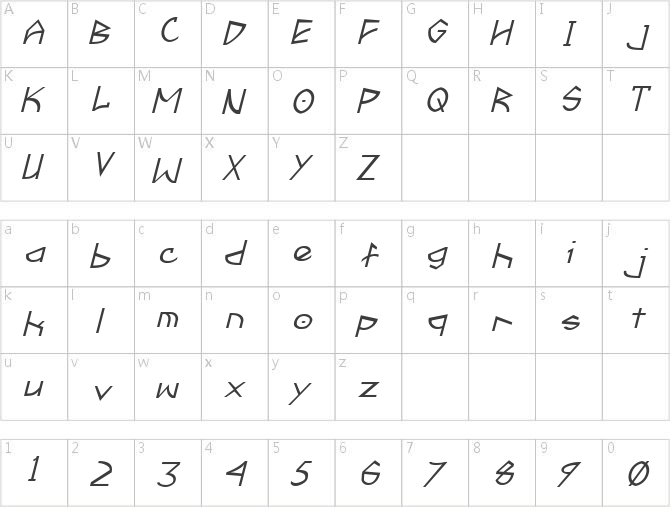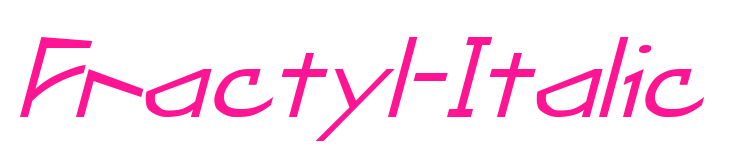
Fractyl-Italic 詳情頁(yè)
字體名稱: Fractyl
Fractyl-Italic
Fractyl-Italic字體字庫(kù)是一款讓人賞心悅目、百看不厭的英文字體,適合各類廣告和產(chǎn)品包裝設(shè)計(jì)應(yīng)用,字體大小0.03MB,格式為ttf字體,上傳用戶是gagilang,作者/版權(quán)方為未知